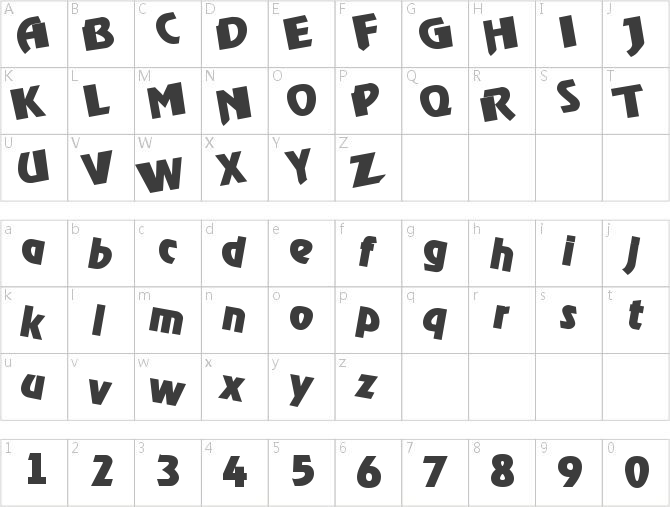
OMEGA Boldo Rocko 詳情頁(yè)
OMEGA Boldo Rocko字體字庫(kù)是一款讓人賞心悅目、百看不厭的英文字體,適合各類廣告和產(chǎn)品包裝設(shè)計(jì)應(yīng)用,字體大小0.06MB,格式為ttf字體,上傳用戶是我,Dirac,作者/版權(quán)方為未知